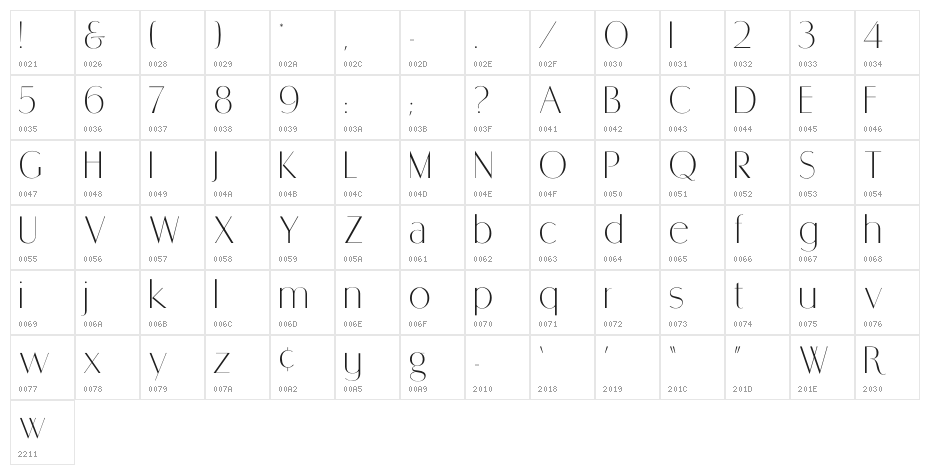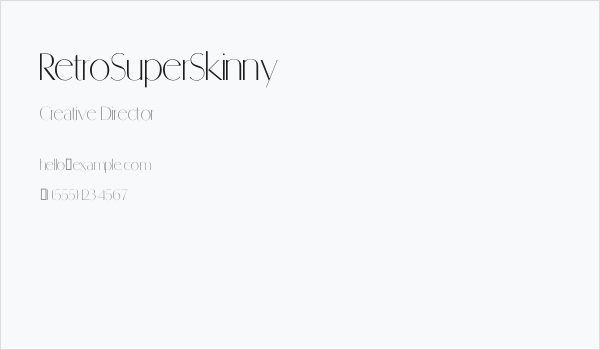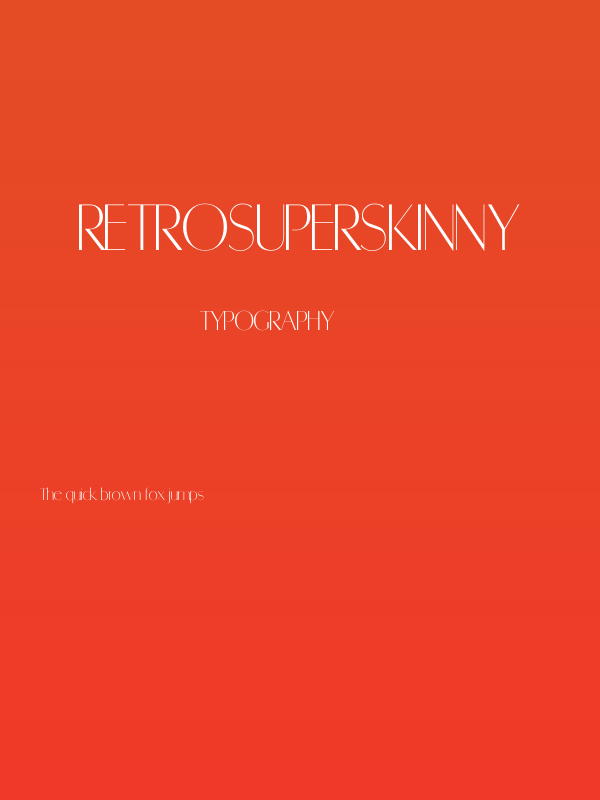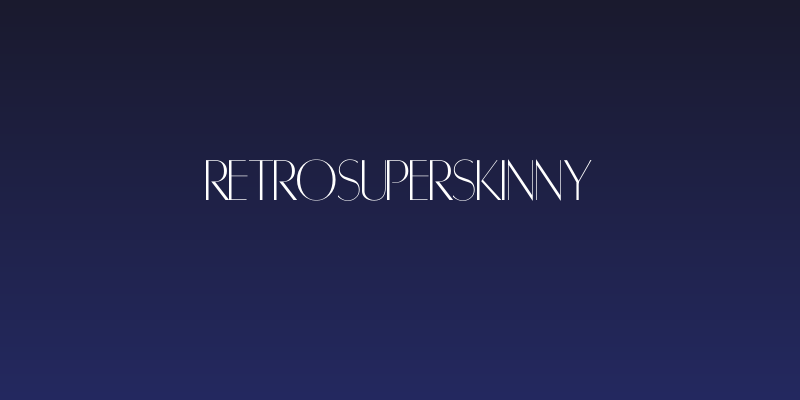
RetroSuperSkinny Font
✎ Calligraphic
| श्रेणियाँ | Calligraphic |
| चौड़ाई | Condensed |
| कंट्रास्ट | High |
| उपयोग का मामला | Headlines, Logos |
| सुझाए गए प्रोजेक्ट | Ideal for fashion magazines, luxury branding, elegant invitations, and modern web design. |